Default typefaces預設字型排印
字型排印幫助文字清晰易讀且美觀
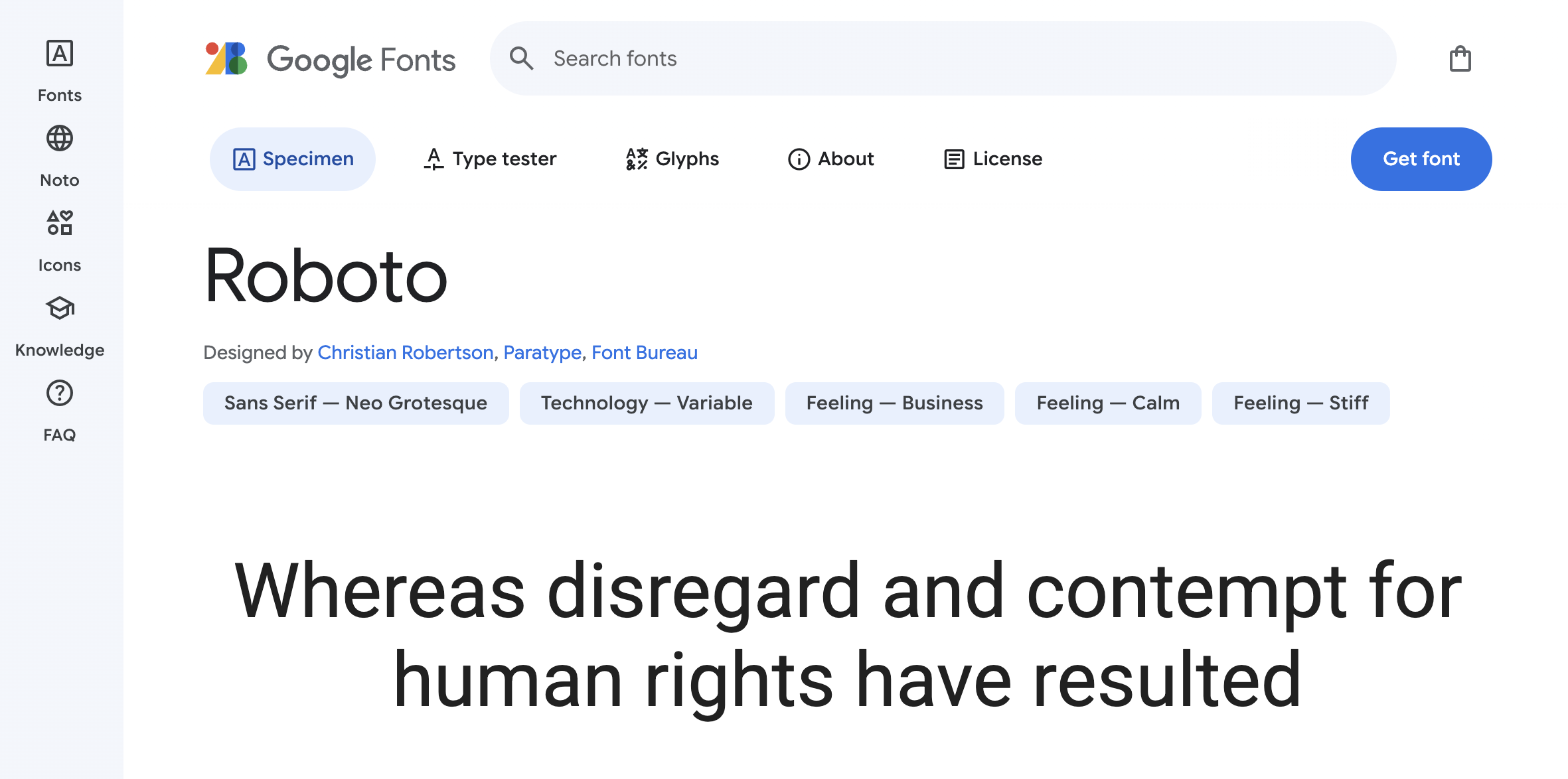
1. Roboto
- Android 預設字型,包含3,300 多個字元,可支援多種語言。
- Roboto Flex 是 Roboto 的可變字型版本,提供更廣泛的字重(weight)、寬度(width) 和可定製屬性(如針對特定尺寸最佳化)。
- 額外支援 拉丁(Latin)、希臘(Greek) 和 西里爾(Cyrillic) 字母。
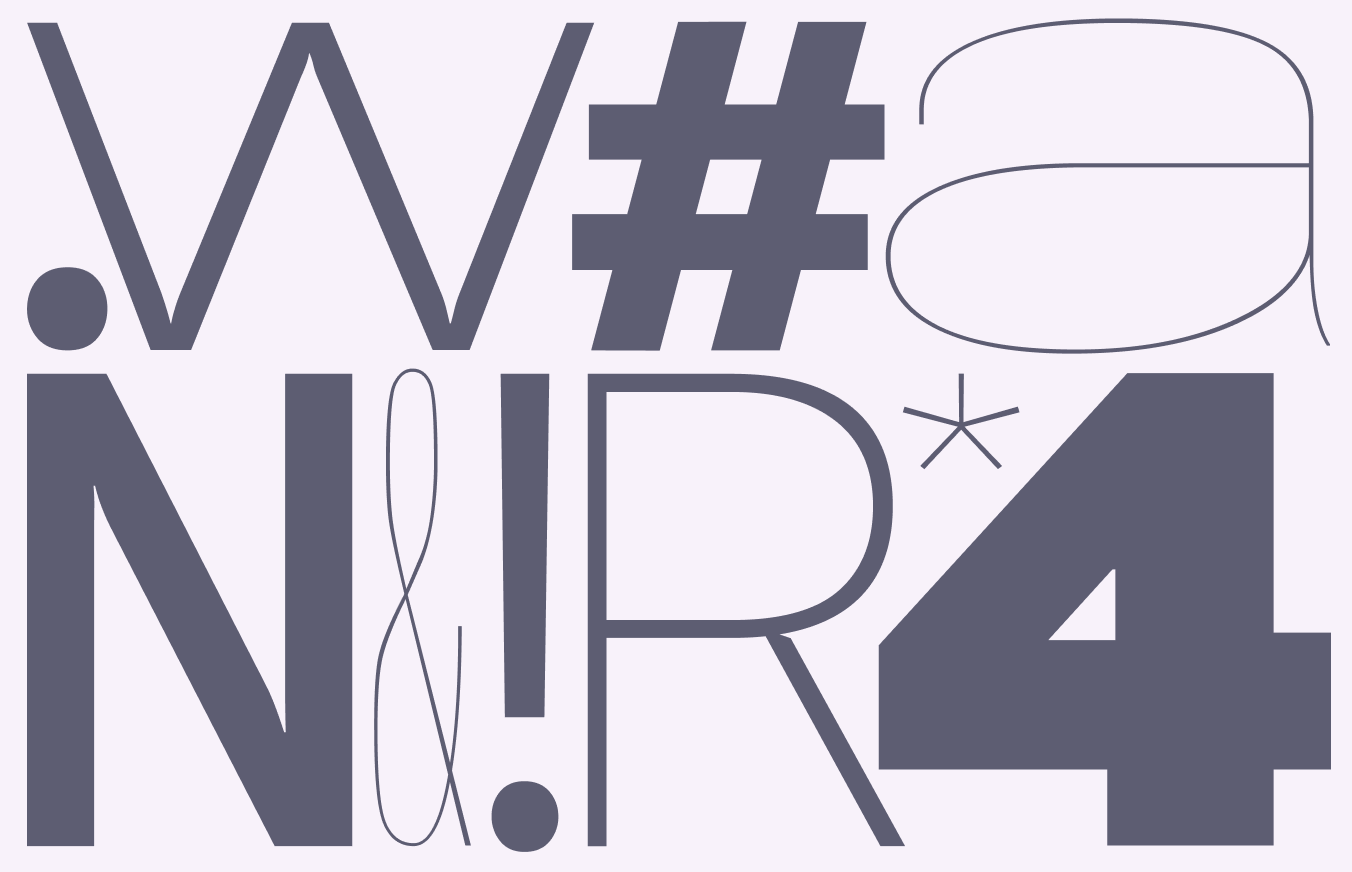
2. Roboto Serif
- 可變字型家族,強調舒適的閱讀體驗。
- 極簡設計,適用於應用介面(UI),可根據不同需求調整字重和寬度。
Roboto Serif 提供多種字重和寬度,使其適用於不同的排版需求。
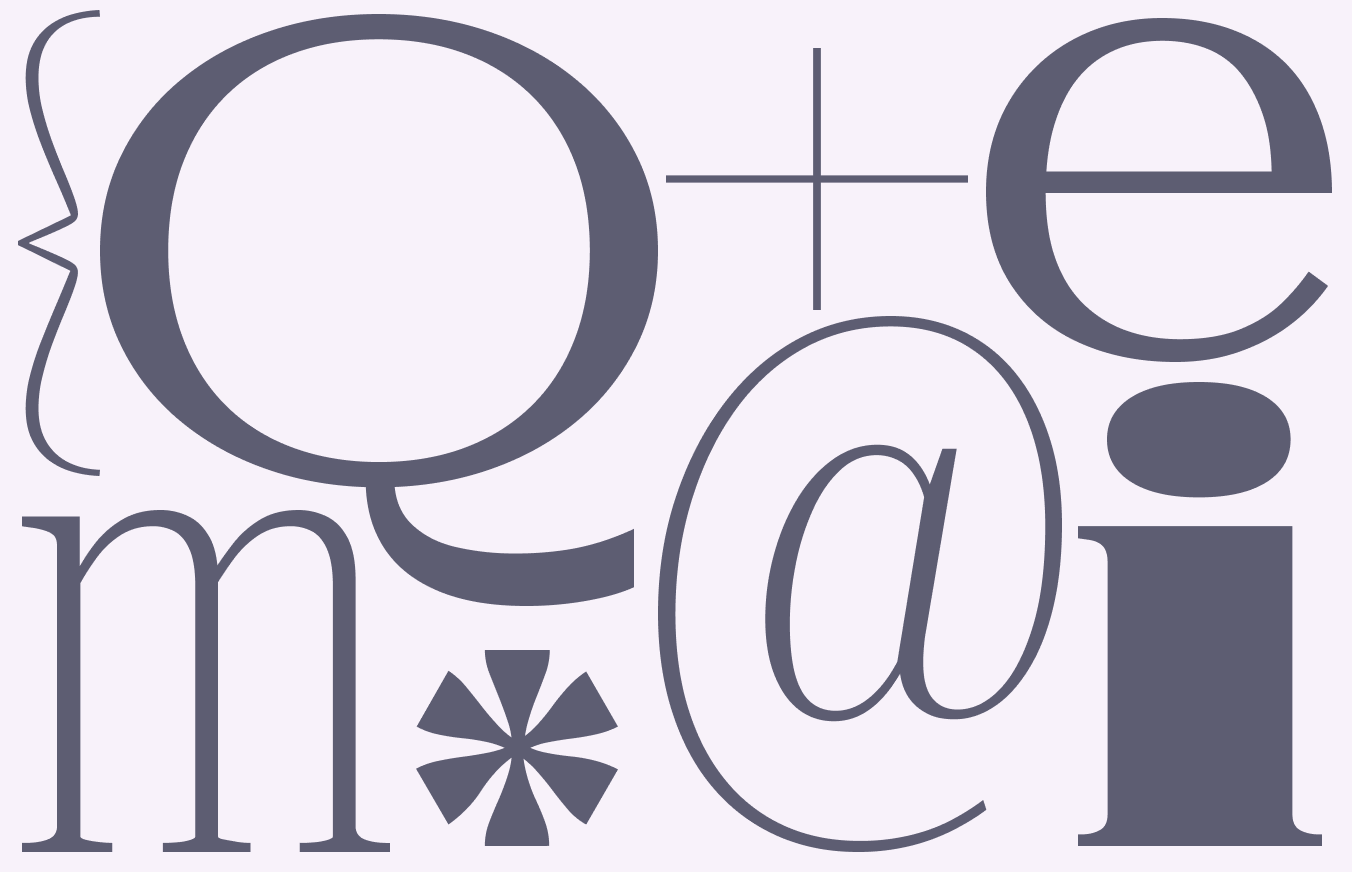
3. Noto
- 全球字型集合,支援現代及古代語言。
- Noto Sans 相容 Roboto,可顯示150 多種書寫系統和數千種語言。
- 作為“後備字型”使用,當某種語言未被支援時,Noto 確保文字不會出現“⯑”方塊(即亂碼)。
Noto Sans 覆蓋多種語言系統,適用於不同書寫方式的文字。